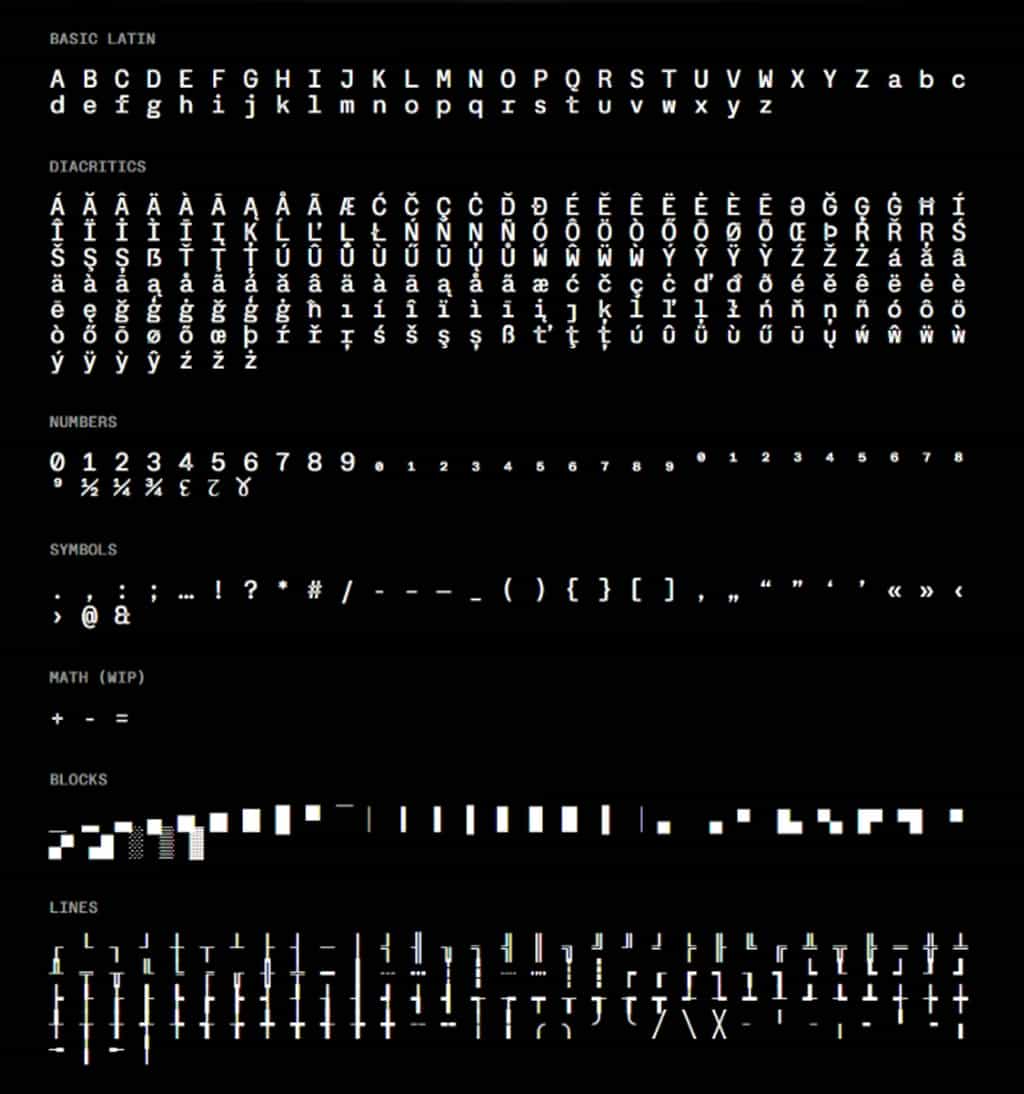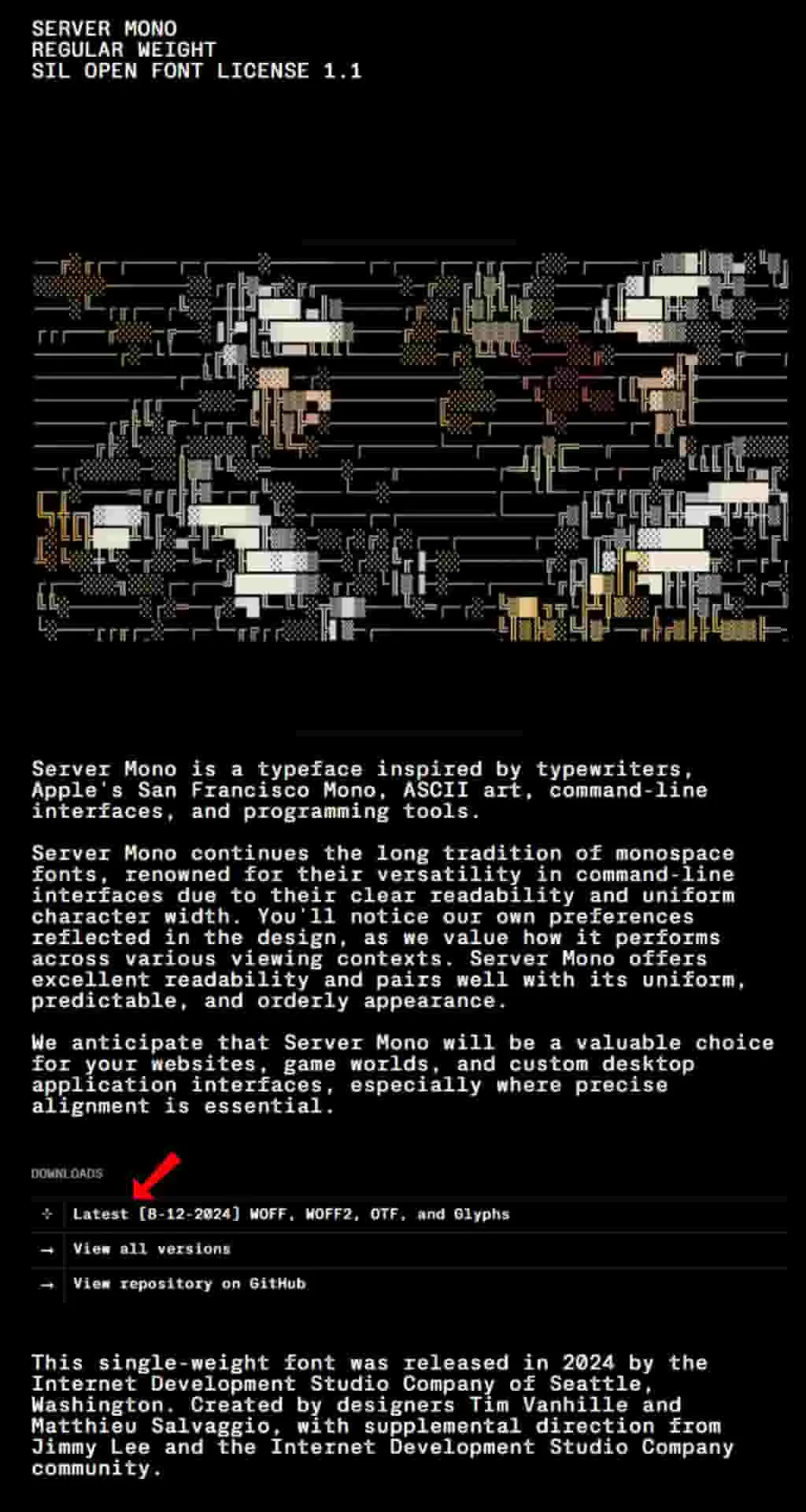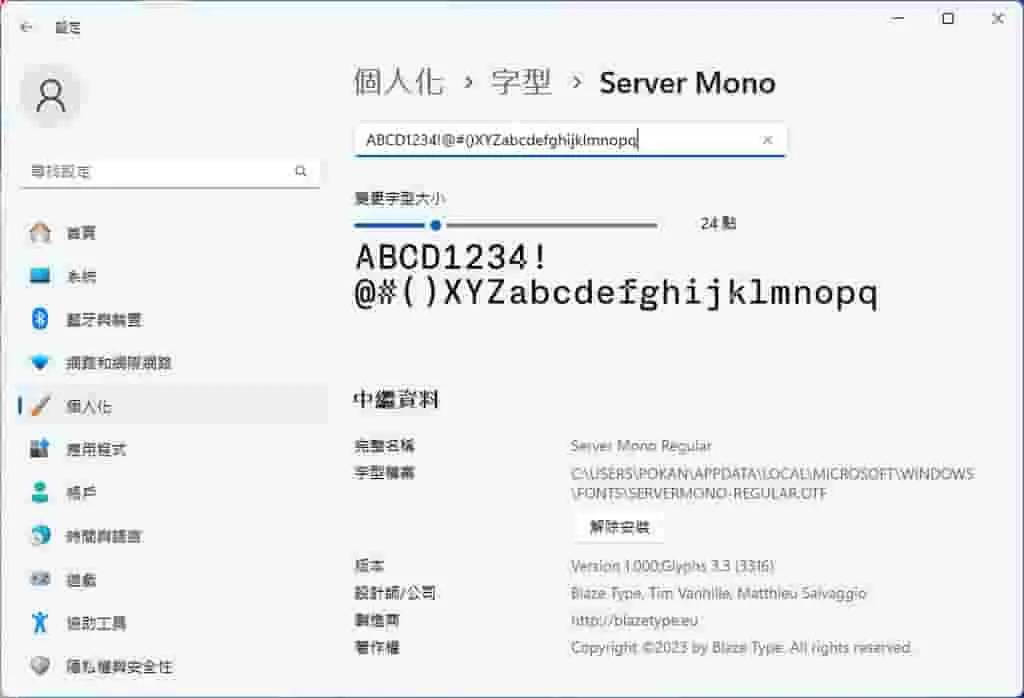
Server Mono 是一個受到打字機字型、Apple 平台的 San Francisco Mono 字型、ASCII 藝術、命令列介面及程式設計工具啟發而開發的等寬英文字體。這個字型具有清晰的可讀性、統一的字元寬度,以及可預測且有序的外觀,使其在命令列介面和其他需要精確對齊的設計文案中廣泛應用。Server Mono 採用 SIL OPEN FONT LICENSE 1.1 授權,允許商業用途,並可自由使用、分發和修改這個字體。該字體僅提供單一字重,是一個適合在各種視覺環境中使用的理想字體。